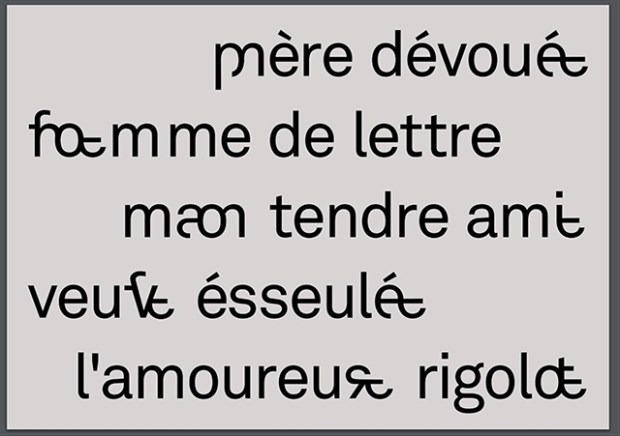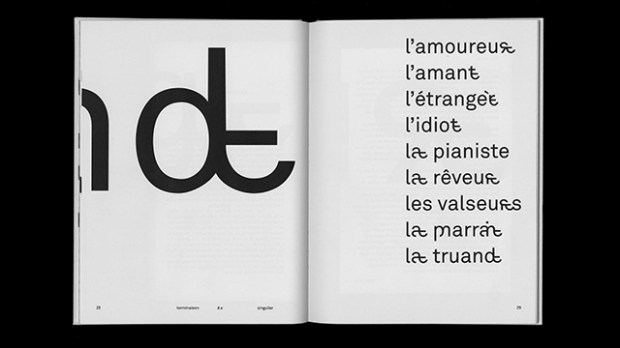
La rédaction épicène ou plus communément appelée écriture inclusive est une méthode destinée à ne produire aucune discrimination sexiste. Mais bien souvent, elle provoque des phrases à rallonge qui deviennent souvent disgracieuses et parfois même incompréhensibles. Pour remédier à cela, le jeune designer, encore étudiant à la HEAD de Genève, Tristan Bartolini a imaginé une typographie d’un nouveau type, incluant des caractères jusqu’ici inédits !
Un travail de graphiste très intéressant qui a poussé le designer à donner naissance à de nouvelles lettres. Par exemple, il a regroupé au sein du même caractère typographie le « e » et le « a » de « le » et « la » pour ne former qu’un seul signe ! Ce sont plus de 40 caractères non genrés qui ont été dessinés par le créatif. Soyons clairs, écrire «l’inclusif-ve», ce n’est pas très satisfaisant d’un point de vue purement esthétique, voici une des raisons qui a poussé le designer à mettre au point ces nouveaux caractères. Mais la principale motivation de Tristan Bartolini était avant tout d’œuvrer pour un monde meilleur et plus inclusif.
Pour la Tribune de Genève, ce graphiste passionné de typo revenait sur sa création : «Je cherchais un thème d’étude au service d’une cause, en accord avec mes engagements et convictions. L’idée m’est tombée du ciel. Il y avait beaucoup de débats autour de l’écriture épicène. Elle devenait de plus en plus fréquente dans les documents administratifs, les publicités. Je me suis dit que ce n’était pas qu’une affaire de linguistes, que l’on pouvait amener des solutions graphiques. J’aimerais que ce projet ne soit qu’un début. Ce système de caractères peut s’adapter à d’autres polices d’écriture. Dès lors, ce serait bien que des typographes intègrent mes signes dans leurs propres créations. J’ai simplement créé un outil de communication. D’autres pourraient l’utiliser pour faire passer un message.»
Un travail de création qui s’est axé autour de deux axes principaux : la visibilité et la lisibilité de ces nouveaux caractères. Ainsi, leur design semble évident, pratique, simple à utiliser. Une belle réussite qu’il nous tarde de pouvoir utiliser sur nos claviers, qui sait, peut-être dans quelques années ?
Pour son projet de typographie épicène, Tristan Bartolini a remporté le Prix Art Humanité 2020 de la Croix Rouge Suisse.